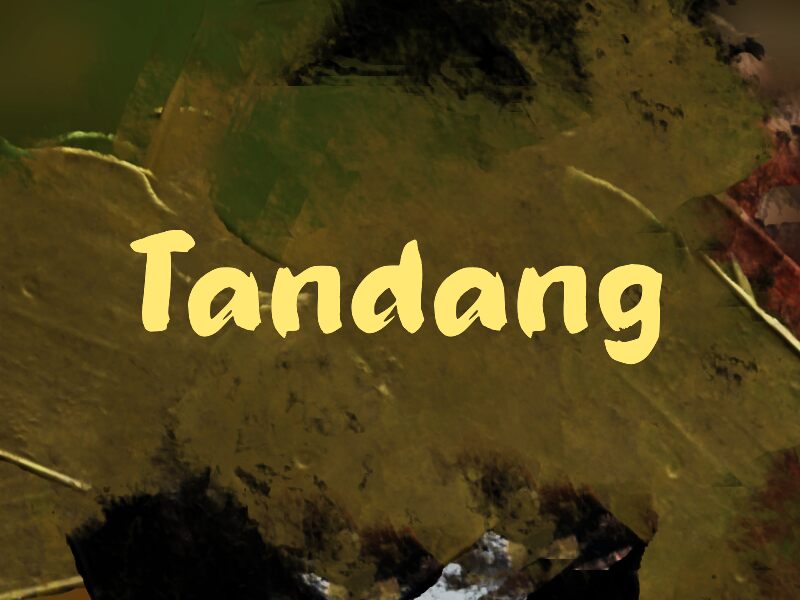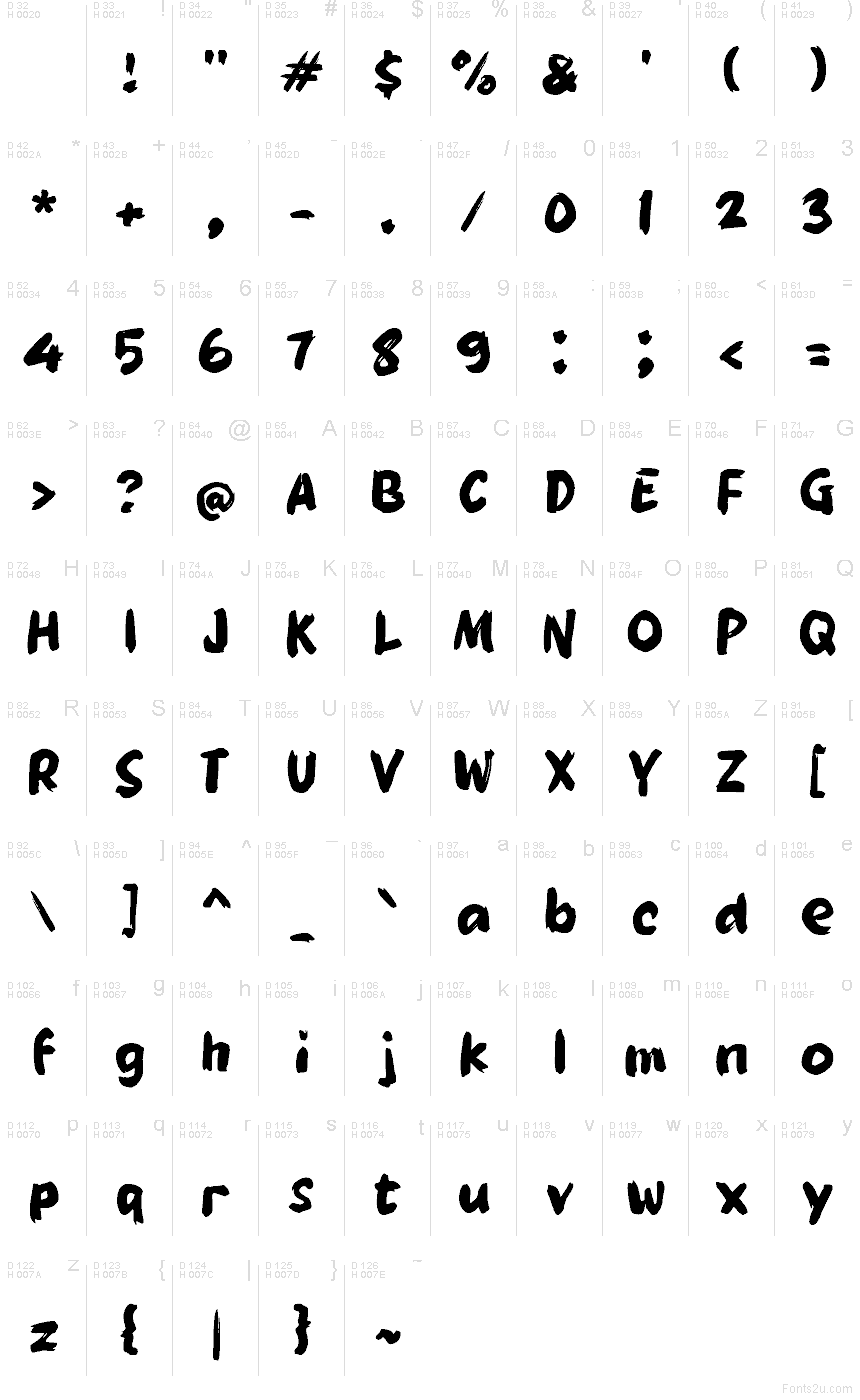
Tandang, créée par Wep, est une police pinceau gratuite au style peint à la main, tout en rondeur et en générosité. Les lettres semblent tracées à la brosse large : départs francs, traits épais et petites pointes pleines de vie qui cassent la rigidité habituelle pour un rendu organique et rythmé.
Idéale pour les affiches, l'identité visuelle de cafés, le packaging, les flyers d'événements ou les titres qui demandent du caractère sans trop de sérieux. En tant que police gratuite, Tandang est parfaite pour les génériques ou les citations courtes, car la densité de ses formes donne une présence immédiate et authentique aux mots.
Tandang